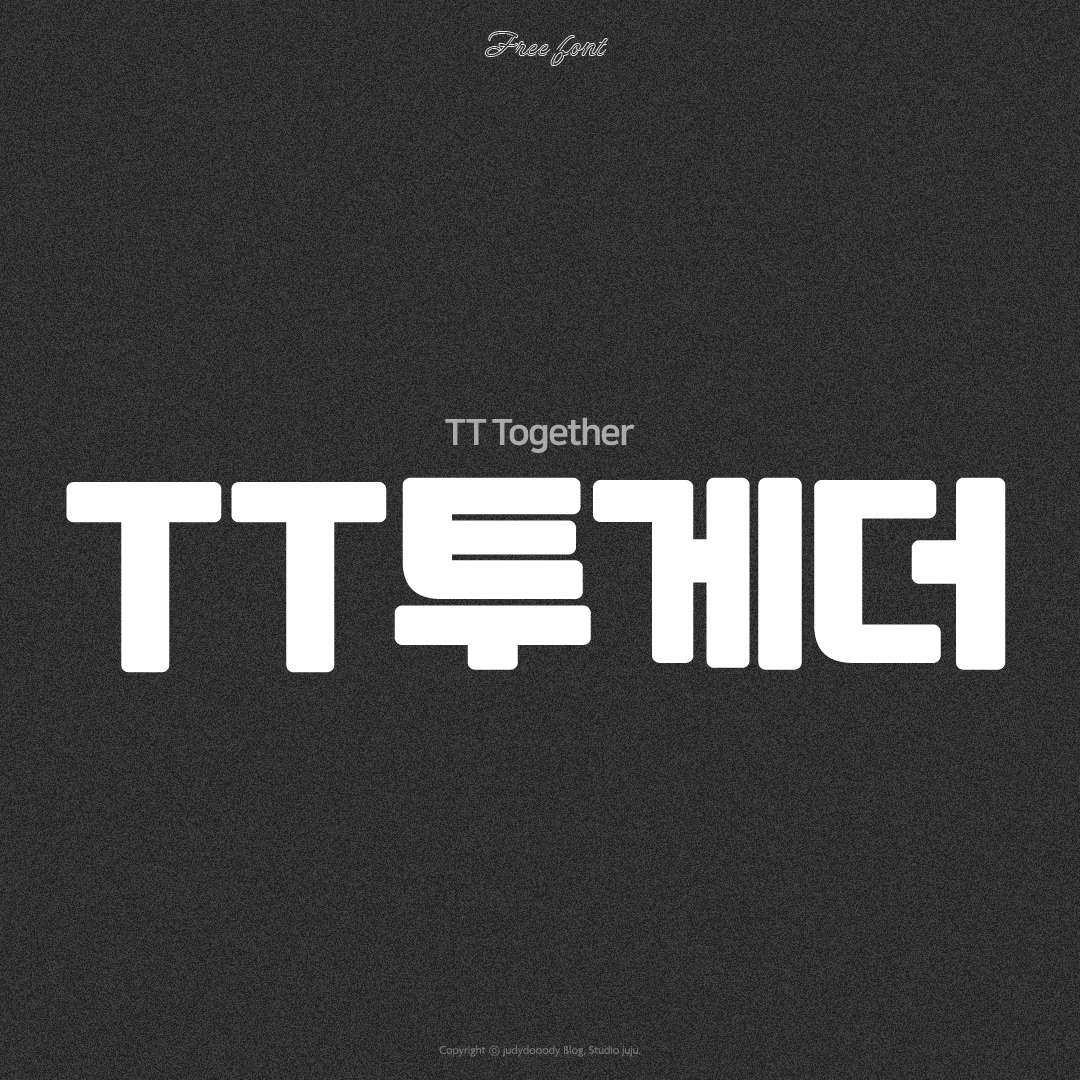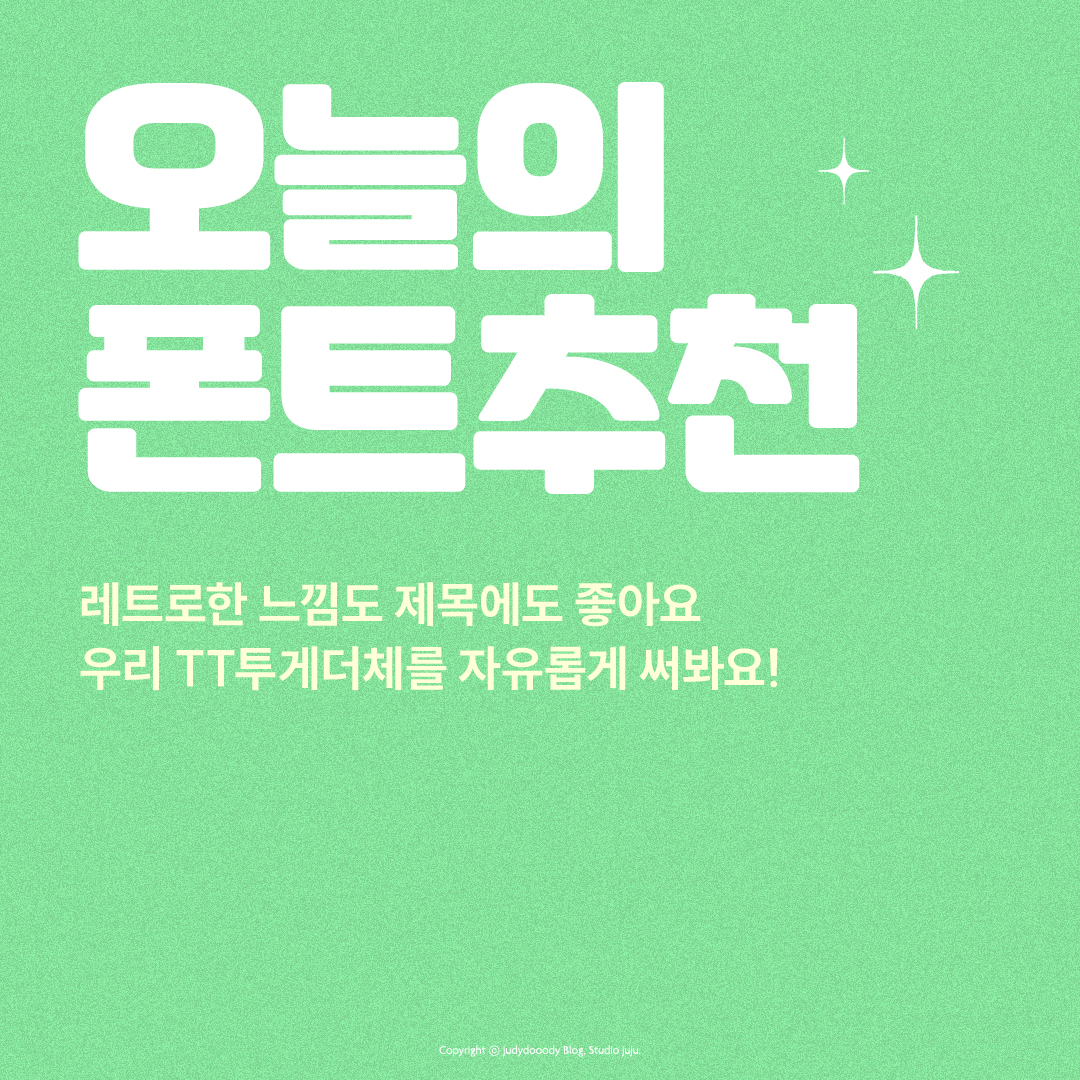
TT투게더체가 아이스크림 투게더인줄 알았는데, 아니었어요 (충격)
글꼴디자인 그룹인 '(주)투게더그룹'에서 배포한 서체였는데요!
잘 알고있는 TT투게더체 외에도 다양한 기업전용서체를 많이 개발한 전문적인 회사더라구요.
요즘 귀엽게 많이 쓰이는 영덕군 전용서체
'영덕대게체, 영덕해파랑체, 영덕블루로드체, 영덕바다체'를 비롯해서
서강대학교의 서강체, 경북대학교 경북대진리체 등
탄탄하게 잘 만들어진 서체들을 많이 만들어낸 글꼴 기업이라
투게더체 역시 너무 탄탄하게 잘 만들어진 서체입니다.
산세리프 San serif
고딕류, 제목
사용 예시
스튜디오주주 디자이너가 알려주는 TT투게더체의 활용 방법을 보고,
여러 디자인에 사용해보세요!
제목용 폰트로 사용하기에도 너무 좋고,
레트로한 복고 느낌을 내기에도 좋은 폰트 입니다.